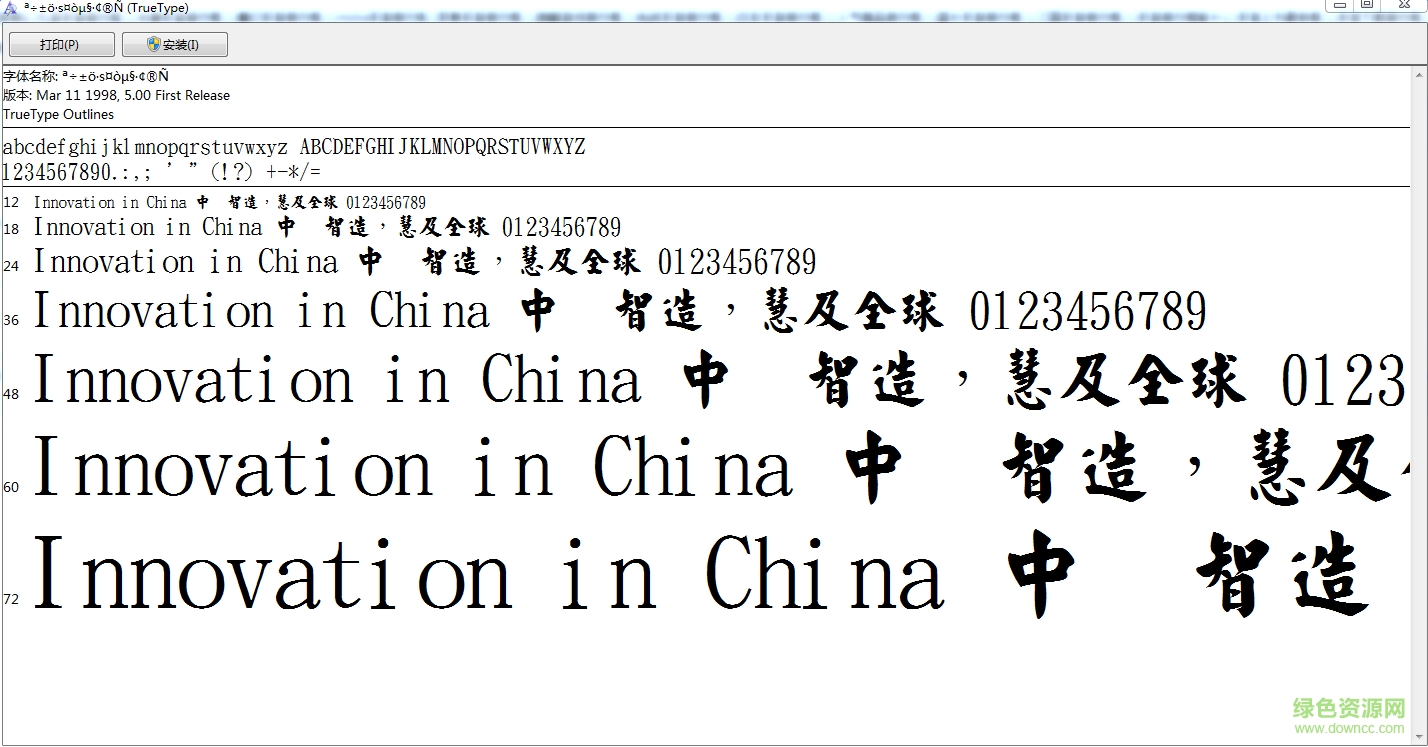
軟件介紹 軟件標簽: 金梅新毛筆楷書 金梅字體 金梅新毛筆楷書字體是一款非常漂亮的金梅字體,該字體筆畫粗細適中,字形俊秀,可應用于出版印刷、商標用字、商業(yè)網站、影視影像視頻等各個領域,有興趣的小伙伴快來綠色資源網下載吧!字體安裝說明1.在綠色資源網下載字體包,并解壓縮2.最簡單的安裝方法:雙擊字體文件,點擊安裝按鈕即可2.批量安裝方法:將字體文件放到C:\Windows\Fonts注意事項本站所有字體資源僅供個人學習與參考,如需商業(yè)使用請到相關官網授權。 軟件截圖 上一張下一張(1 / 1) 安裝詳細截圖 猜你喜歡 商業(yè)字體 藝術字體 商業(yè)字體是應用在商品包裝、平面設計、影視設計、雜志報刊、印刷排版等領域的字體,涵蓋了柔美的、古韻的、現代感等不同風格的字體,可適用于各種商業(yè)領域! 查看更多>> hiragino sans gb w6字體 10.15M/中文/7.0/下載 hiragino sans gb w3亮體 16.60M/中文/3.8/下載 電腦字體奇思楷體 2.92M/中文/10.0/下載 ubuntu字體合集 1.68M/中文/6.0/下載 universltstd英文字體 23KB/中文/10.0/下載 roboto字體 991KB/中文/10.0/下載 藝術字體 藝術字體下載大全免費打包專題是小編專為廣大字體控朋友們整理的經典藝術字體大合集,包含了各式各樣的書法藝術字體和個性藝術字體,整體效果十分出眾! 查看更多>> 華為伯樂油畫體 2.05M/中文/10.0/ttf免費版下載 鄭板橋書法字體 795KB/中文/0.0/下載 孫過庭草體測試版 1.37M/中文/10.0/下載 淡齋草書字體 2.92M/中文/8.5/下載 白舟太篆書體字體 2.36M/中文/3.3/下載 白舟靜月書體字體 1.12M/中文/10.0/下載 其他版本下載 標題 大小 更新日期 下載 下載地址 電腦版 金梅新毛筆楷書 點擊報錯 軟件無法下載或下載后無法使用,請點擊報錯,謝謝! 關閉報錯反饋 請描述您所遇到的錯誤,我們將盡快予以修正,謝謝! *必填項,請輸入內容 本類最新 金梅海報美工體 金梅新箭頭字范例字體 免費版 金梅特黑水花字形字體 免費版 金梅粗尖頭字范例繁體字體 免費版 金梅淡古字ttf 免費版 金梅浪漫鏡射體 用戶評論 熱門評論 最新評論 發(fā)表評論 查看所有評論(0) 昵稱: 請不要評論無意義或臟話,我們所有評論會有人工審核. 字數: 0/500 (您的評論需要經過審核才能顯示)